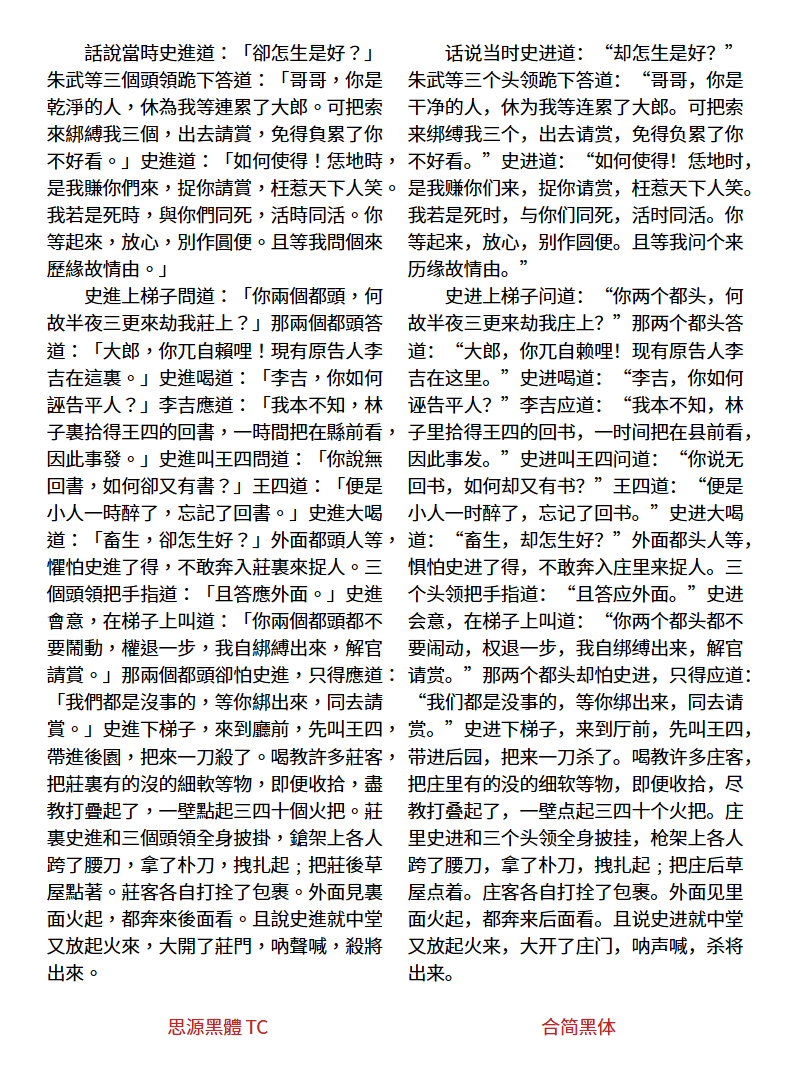
HeSimpl Sans 合简黑体
HeSimpl Fonts 是一套基于思源黑体与思源宋体(简体版)开发的繁简转换字体。
该字体能够将繁体内容自动转换为简体,并深度利用 OpenType 技术特性,实现了基于上下文的“一繁多简”动态匹配功能,显著提升了繁简转换的精准度。
字体特性
1. 包含字族
• HeSimpl Sans (合简黑体)
• HeSimpl Serif (合简宋体)
2. 优势
• 动态化匹配:借助 OpenType 特性,字体能够自动在多个简体候选字中选择最准确的一个(如“乾坤”对应“乾坤”、“乾燥”对应“干燥”)。
• CJK 大字库:继承了思源系列极广的字符覆盖率,确保在处理复杂 CJK 文本时几乎无缺字困扰。
效果预览
以下对比图展示了繁体文本的呈现效果:
对比说明: 下图中左侧为 思源黑体,右侧为 合简黑体。
预览文本全部为繁体,取自《水滸全傳》第三回,重点展示了本字体对繁转简的自动转换效果。
思源黑体TC与合简黑体对比图,左侧繁体右侧简体,展示同一段史进文本的字体效果。-刊刻Kntuk